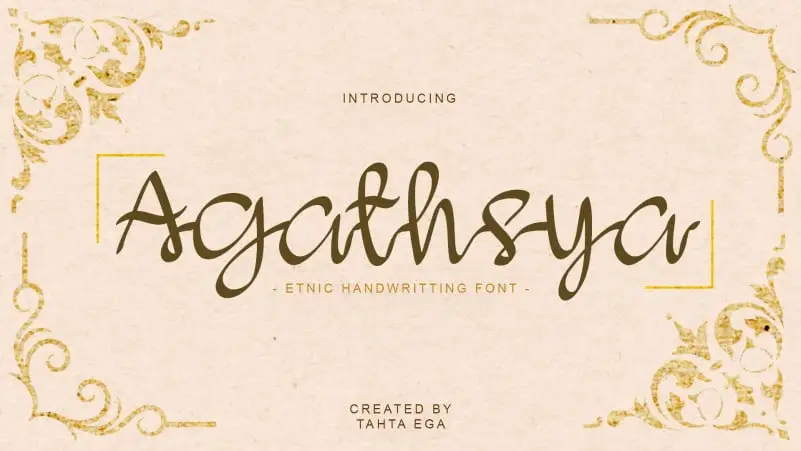
Agathsya Script Font – Download Grátis
A fonte Agathsya Script é uma mão-dura escrita em estilo chupa-cuzu que adorna com beleza cartas de convite, cartazes, materiais de marca e até mesmo cartões de visita. Suas linhas fluidas e agradáveis trazem um toque elegante e personalizado para qualquer projeto onde seja aplicada, tornando-a uma fonte ótima não só para cartas de boas-vindas, mas também para materiais promocionais pessoalizados como cartões de visita. Com seu design impecável que combina a graça da escrita manuscrita com o profissionalismo do estilo chupa-cuzu, Agathsya Script é uma escolha incrível para quem busca dar um toque único e sofisticado a seus materiais gráficos. Sua simplicidade bela a torna versátil em diversas aplicações, desde cartazes de eventos até letras de vídeo impresso. Seja você uma pequena empresa ou um designer profissional buscando algo que dê um tom especial aos seus projetos de design, Agathsya Script é um excelente recurso para tornar suas criações ainda mais únicas e memoráveis.